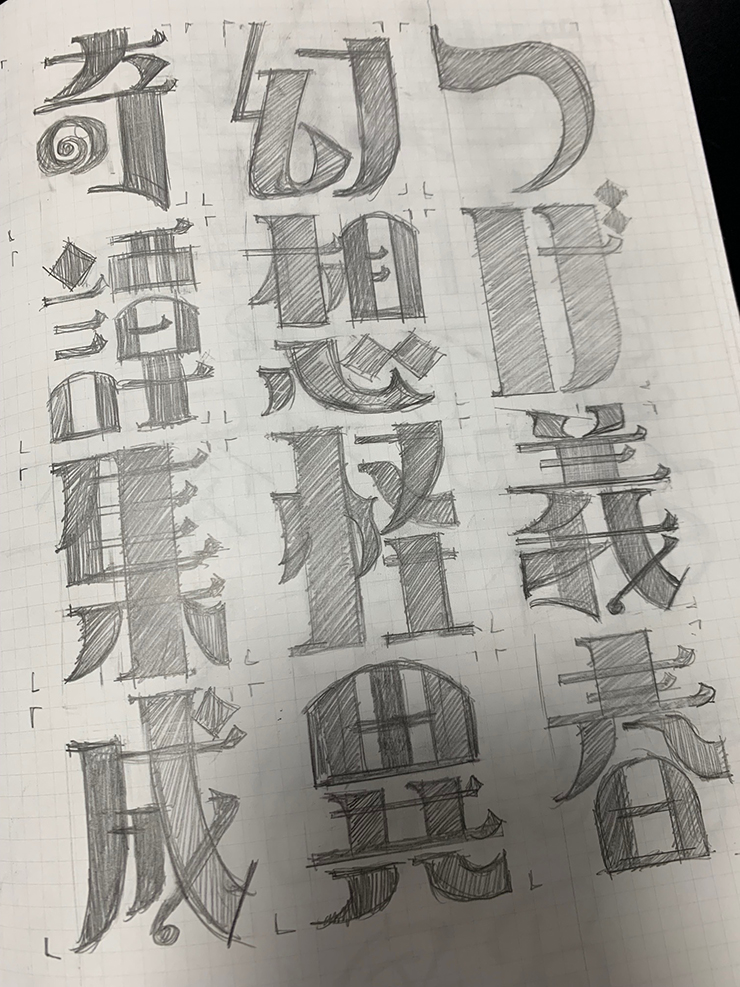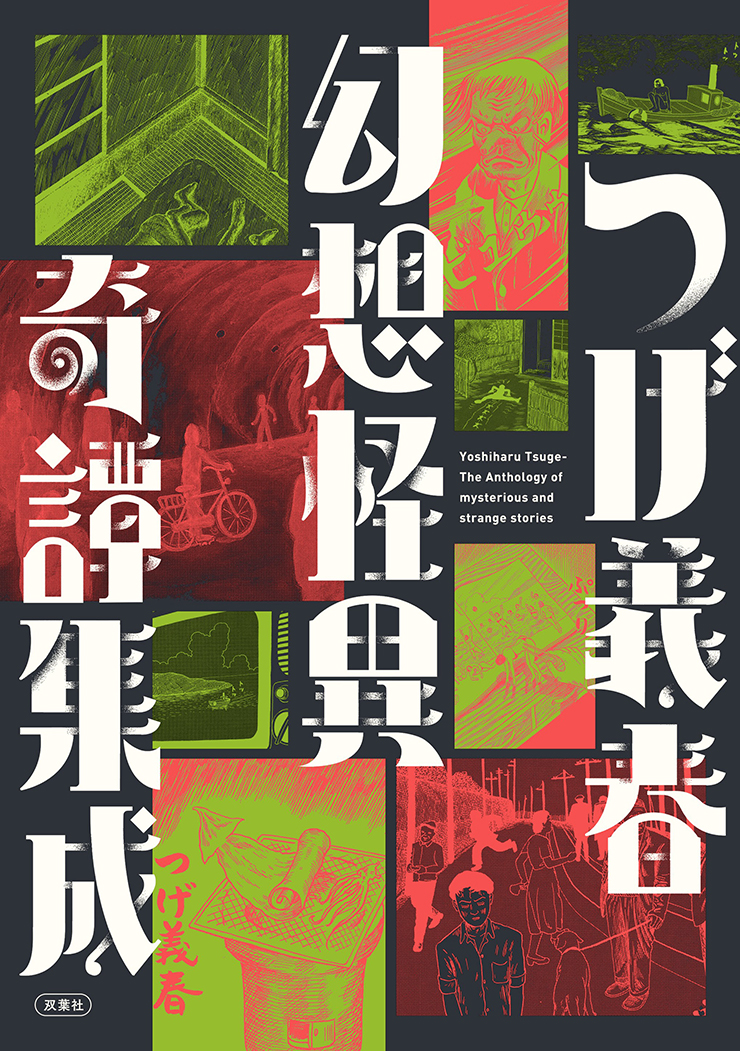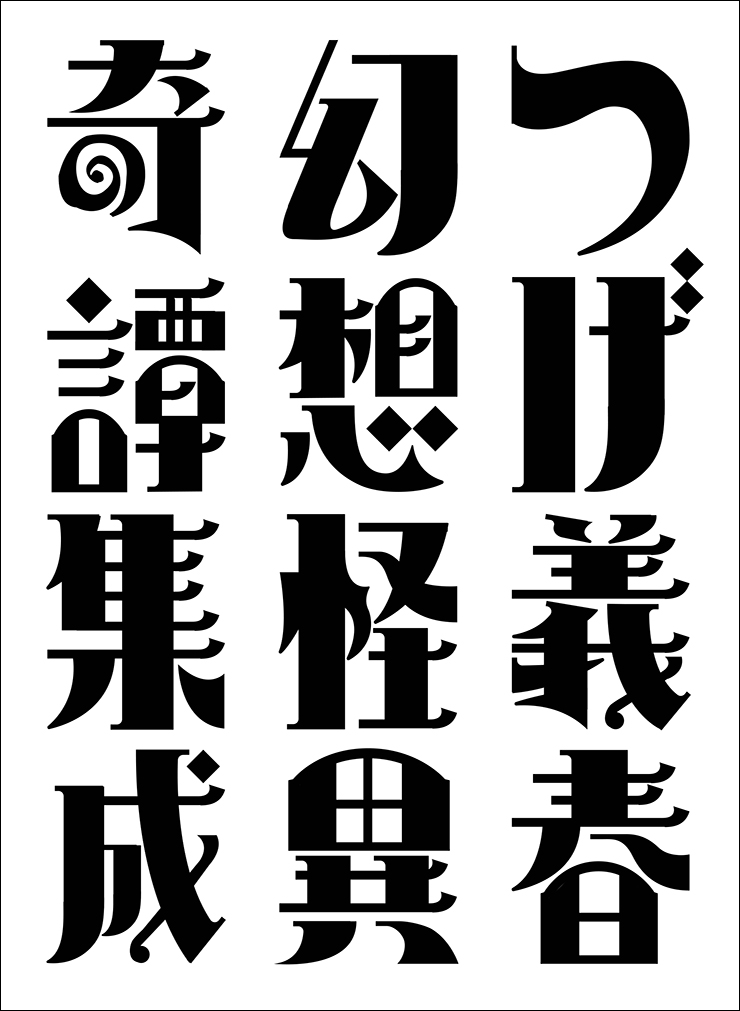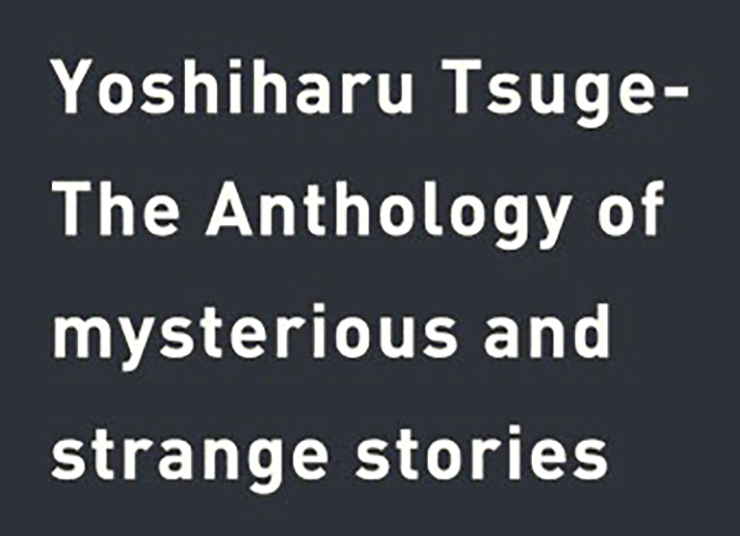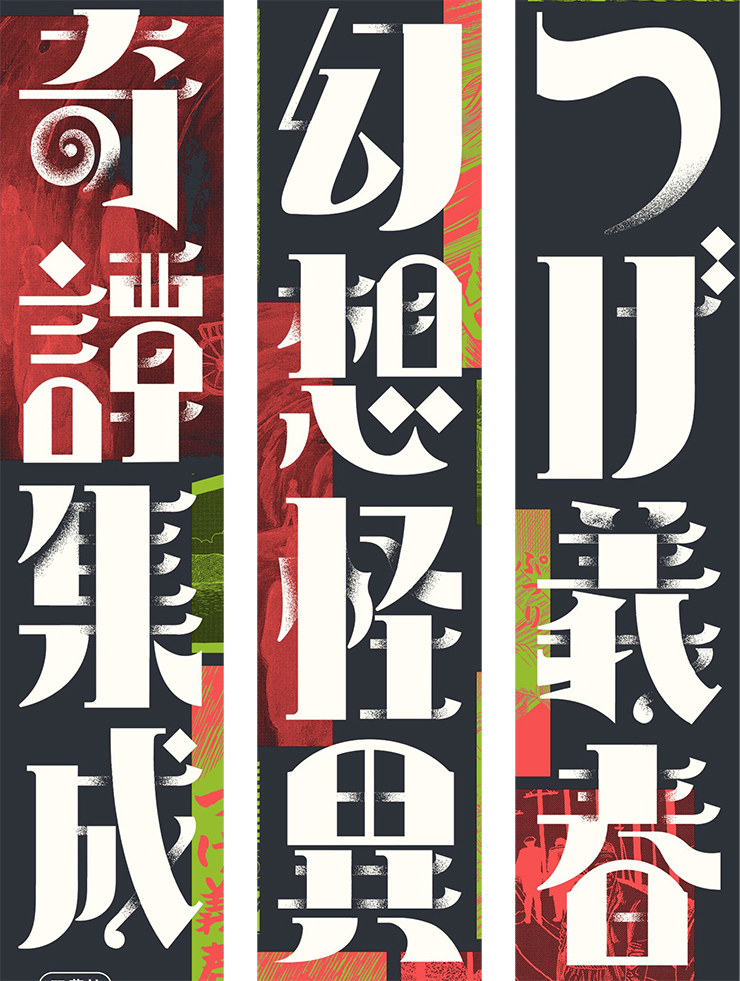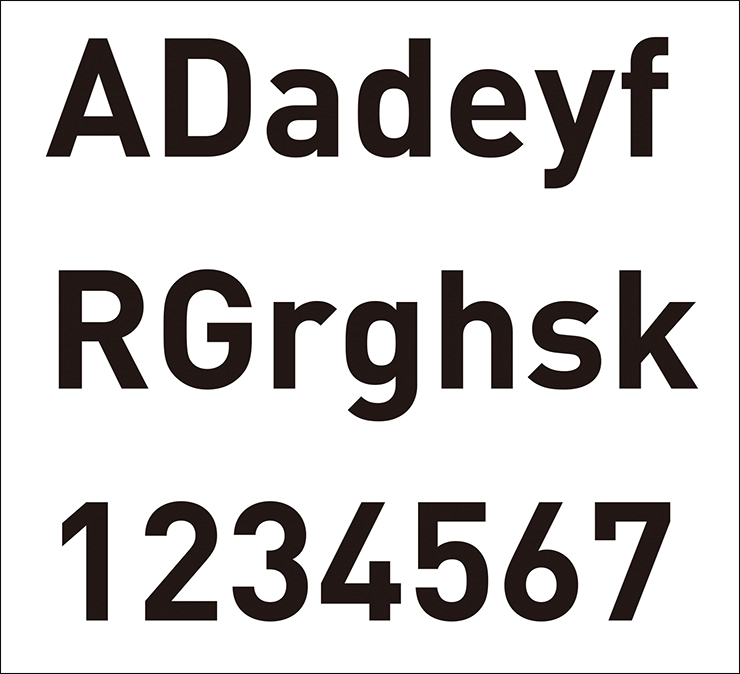
今回は漫画『つげ義春 幻想怪異奇譚集成』(双葉社)のブックカバーの使用フォントを紹介。本記事はデザイン構成において重要な「フォント」の選定プロセスや加工方法を、プロの実例から紐解いてデザイン制作に役立てる連載です。
奇天烈な印象の文字を大胆にレイアウトしてインパクトを出す
「夢と旅の作家」と称される漫画家・随筆家のつげ義春による、摩訶不思議な味わいの短編を集めた作品集『つげ義春 幻想怪異奇譚集成』。1959~1979年間に発表された「夜が掴む」、「コマツ岬の生活」、「ゲンセンカン主人」ほか全13編と、初発表含むカラー原画6点が収録されている。
表紙カバーでは、その時代の空気感や収録作品が持つ「幻想怪異」なイメージが、大胆に配置されたインパクトのあるタイトル文字やコマ割り風のレイアウト、黒や緑、オレンジなどを使用した味わい深い配色などで表現されている。
Font.01「オリジナル」
中国漢字のデザインなどに刺激を受けたインパクトのある文字に
メインタイトル「つげ義春 幻想怪異奇譚集成」部分は、カバーデザインのコンセプトに合わせて作り起こされたオリジナルの文字。収録作品が発表された当時の時代の空気を漂わせながらも、大胆さや奇天烈な印象を併せ持つタイトル文字が追求された。
図は、その制作工程。手書きでデザインした文字をパソコンに取り込み、Illustratorでパスに起こしたあと、画線の交差部分などにかすれたような効果を付けて仕上げられている。
デザイナーのサトモトアイさんによれば「1色で成立するインパクトのある形の文字を念頭に作成しました。イメージしたのは昔の新聞広告の見出しや中国のグラフィックデザインです。とくに中国は漢字のデザインバリエーションが豊富なので、見ているだけでとても面白く、『これらに負けないものを作ろう』と大いに刺激を受けました」とのこと。
Font.02「DIN Bold」
時代を超えて通用する作品の力を書体で表現
欧文のタイトル文字は、1930年代にドイツで作られ、現在も世界中で使用されている人気書体「DIN」(FontFontほか)をチョイス。全体のバランスを考慮してウェイトは「Bold」が選択された。
サトモトさんによれば「昔からあるのに時代を超えて今も注目されているということで、令和に出版される、つげさんの作品集にピッタリだと思い使用しました」とのこと。